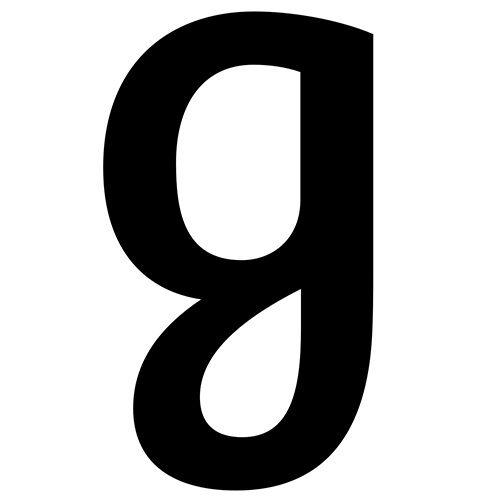
- 2007
- Antiqua humanistisch
Entworfen in den Jahren 2006/2007 von Marconi Lima und 2008 erweitert von Silas Dilworth, liegt mit der Adriane Text eine gut lesbare Textschrift mit den klassischen vier Schnitten (normal, fett und jeweils passende Kursive) vor, die außerdem mit Kapitälchen, Mediävalziffern, Tabellenziffern, hoch- und tiefgestellten Ziffern sowie einer ganzen Reihe von Ligaturen und Symbolen aufwartet (allerdings leider nicht mit Versal-Eszett).
Passend zur Adriane Text gibt es noch die Adriane Lux als dekorative Inline-Schrift mit gleicher Glyphen-Ausstattung und die Adriane Swash mit einer Reihe zusätzlicher Schwungbuchstaben.